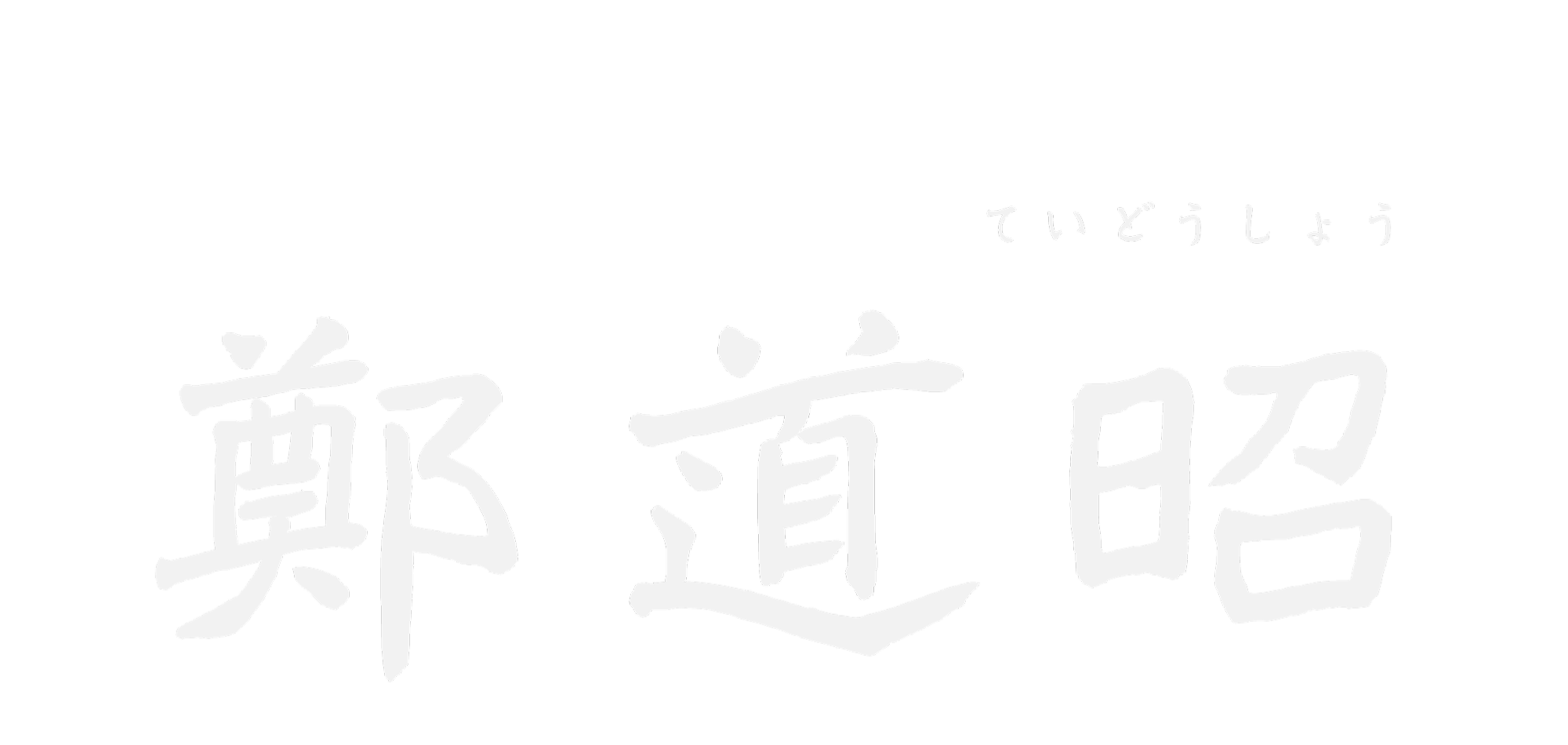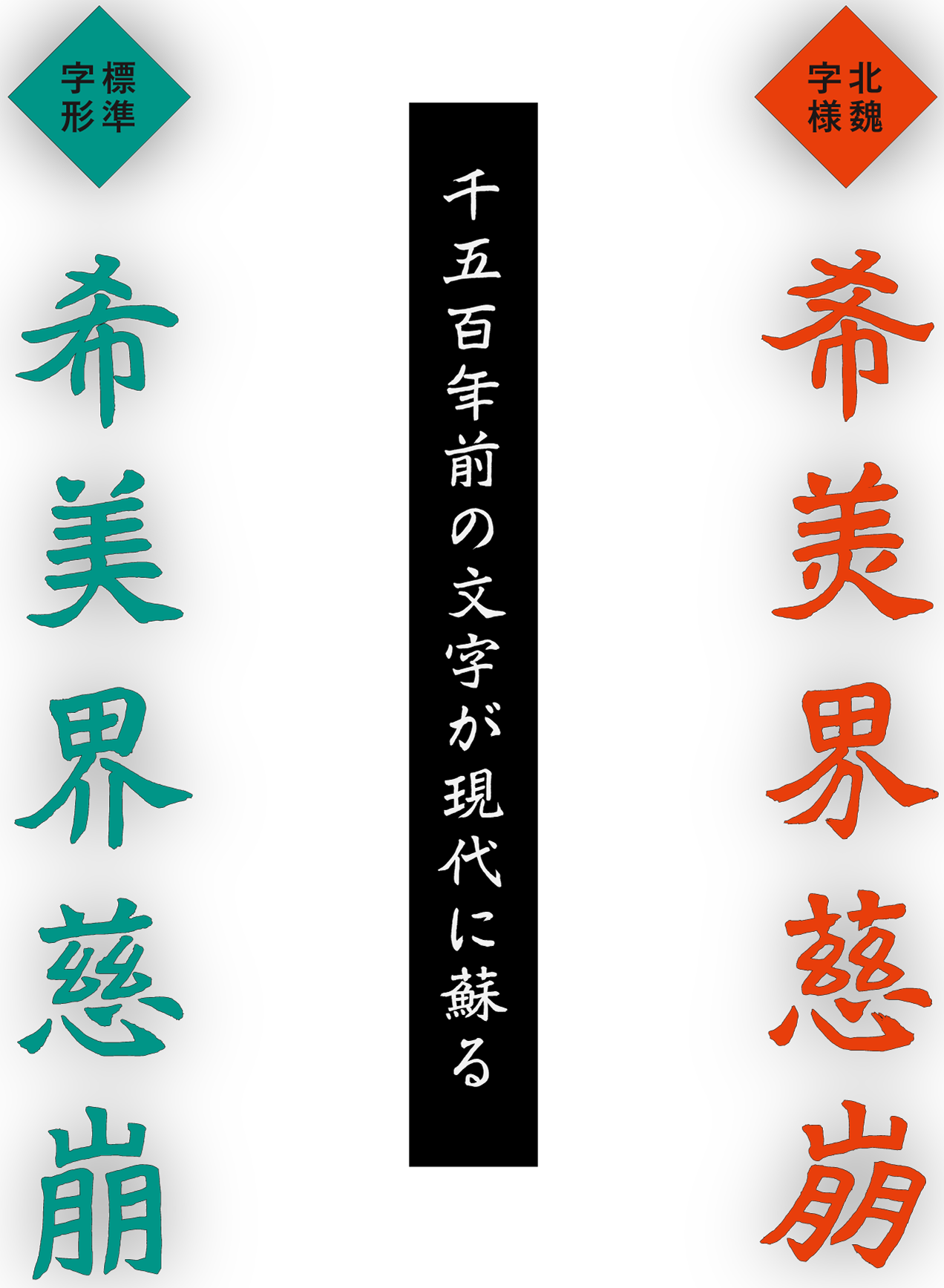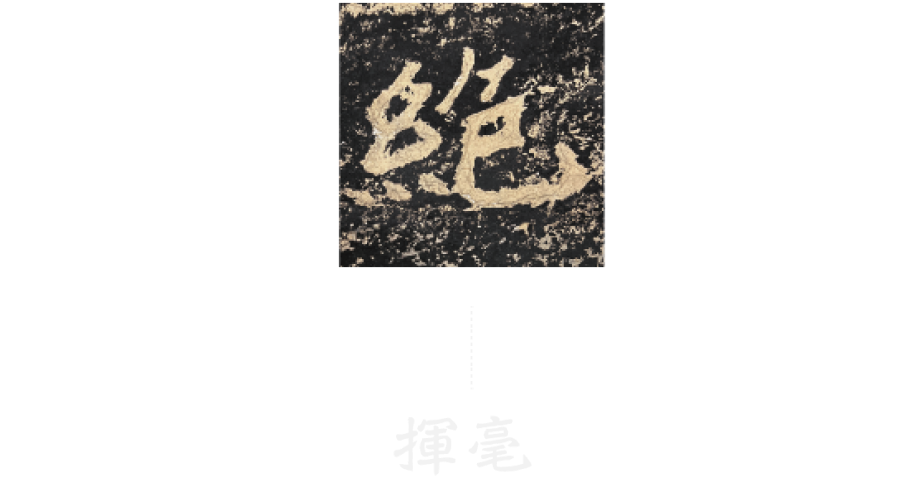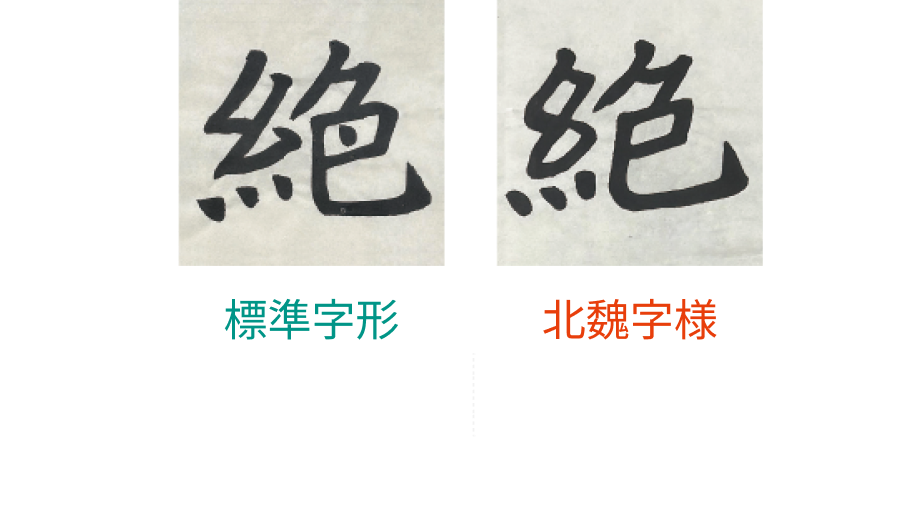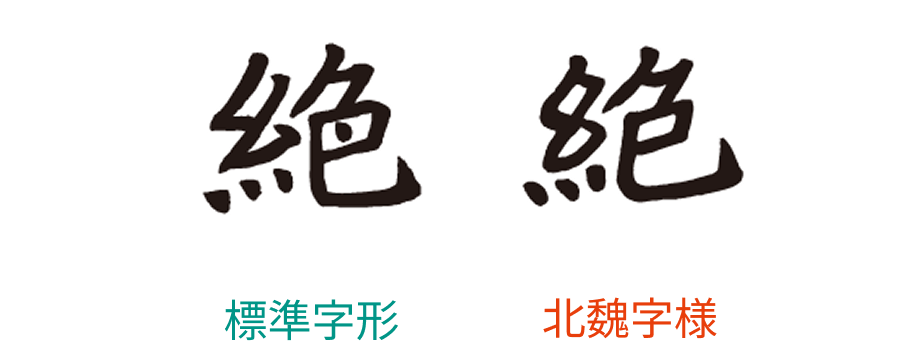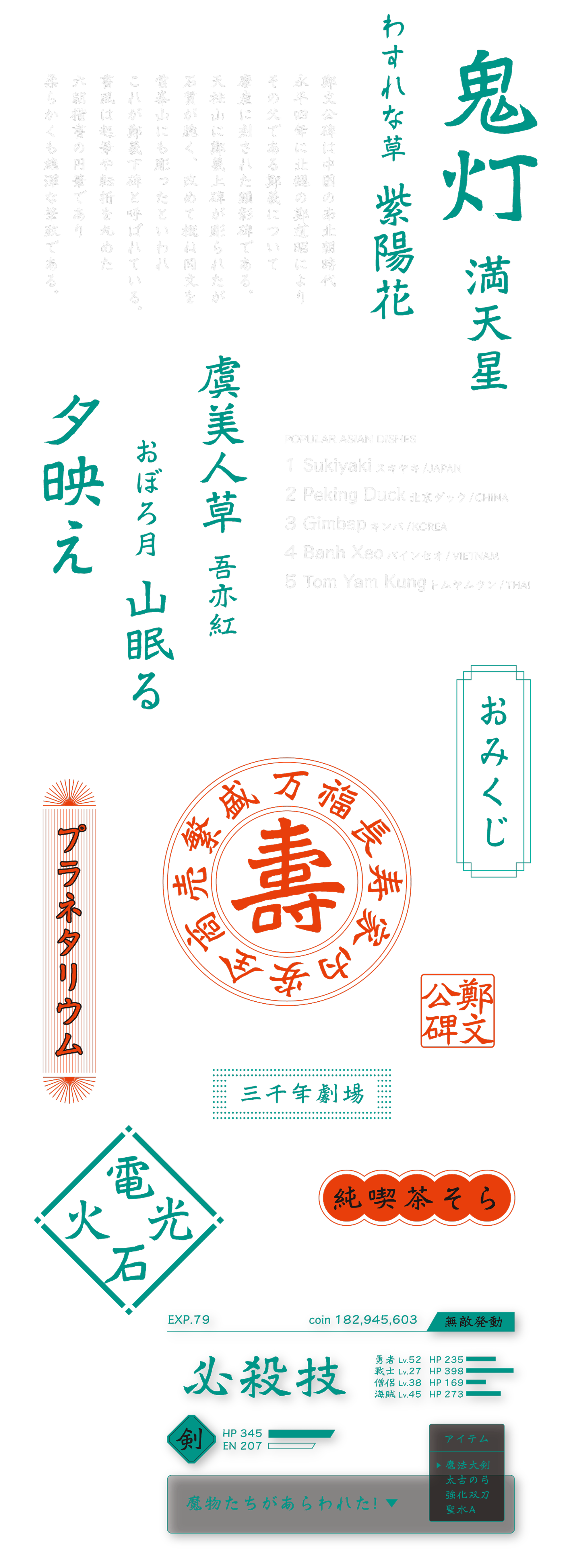
1500年前、中国雲峰山の岩壁に刻まれた鄭道昭の書が現代に蘇る。
摩崖碑の風化や岩肌のニュアンスを封じ込めた書体。
書家・大庭紀霽氏によって書き下ろされた、ゴツゴツとした力強さの中に、
のびやかな骨格の優しさが光る独特のバランス。
雄大な自然や筆の息遣いまで感じる、圧倒的な存在感を放つ書体です。
『鄭羲下碑』をはじめとした鄭道昭の筆跡
現代の標準的な字形だけでなく
拓本に倣った北魏字様も書き下ろし
筆書の勢いをそのままに組みやすいバランスを実現
揮毫  大庭紀霽(おおばきせい)
イワタ鄭道昭 標準字形
イワタ鄭道昭 北魏字様
イワタ鄭道昭